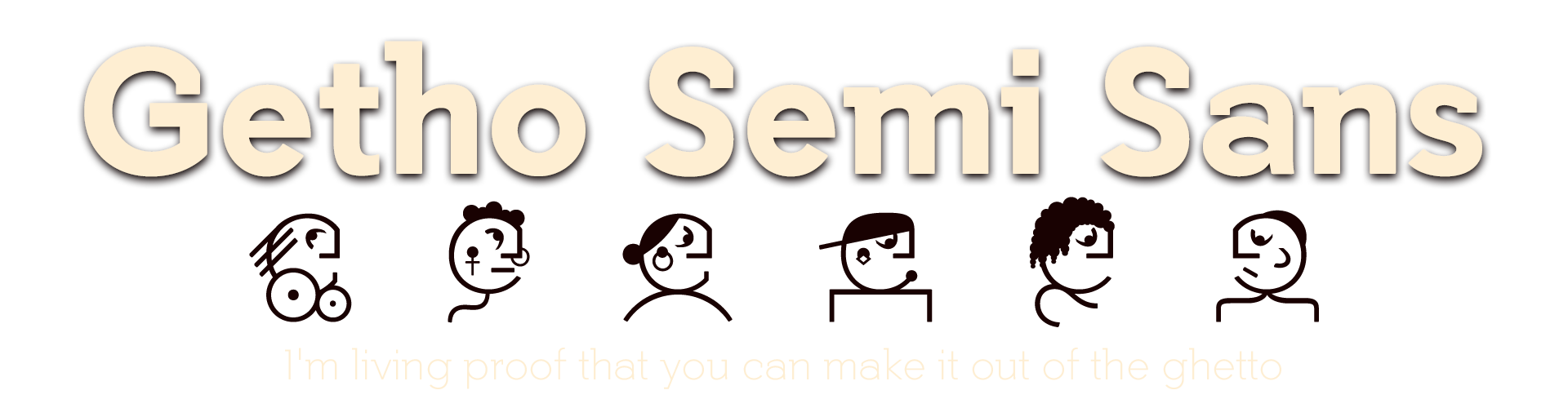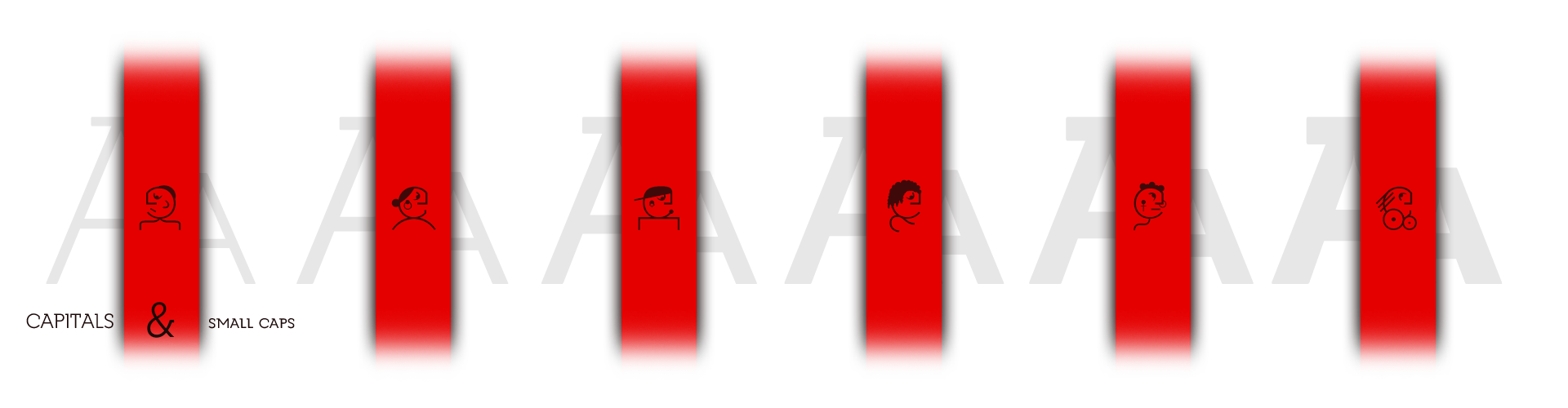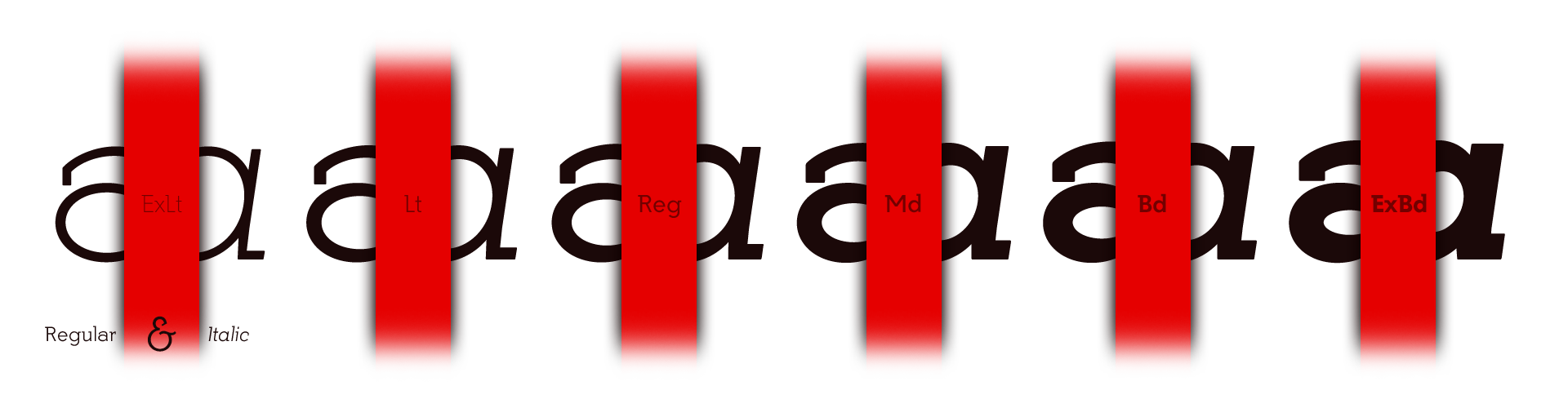
Conceptual typeface
Estilo: Semi Sans, Semi Slab, Versalitas, Geométrica, Corporativa
Proporción: Extra Light, Light, Regular, Medium, Bold & Extra Bold + Italics
Glyphs: 718
Alternates: 181
Funciones OpenType: Additional languages, All Alternates, Alternate Annotation Forms, Capital Spacing, Denominators, Discretionary Ligatures, Extended Fractions, Historical Forms, Historical Ligatures, Inferiors, Kerning, Localized Forms, Numerators, Oldstyle Figures, Optical Size, Ordinals, Scientific Inferiors, Slashed Zero, Small Capitals, Small Capitals From Capitals, Standard Ligatures, Subscript, Superior letters, Superiors, Superscript.
b#) y otros símbolos monetarios.Se trata de una exclusiva tipografía con modulaciones neo-grotescas y máxima legibilidad en cualquier tamaño. La tipografía dispone de letras y números alternativos, versalitas y funciones OpenType avanzadas. He incluido versiones de la tipografía en formato Variable Fonts, sólo con la compra de la familia completa!!
El dibujado de los vectores es minucioso para obtener curvas suaves de aspecto elegante a lo que contribuye también el sutil redondeado de las esquinas, las versiones más gruesas disponen de trampas de tinta en los nudos de las uniones para poder usarlas en pequeños tamaños. La Métrica y el Kerning de todas las versiones las he revisado individualmente para obtener una lectura fluida en cualquier tipo de texto y tamaño.
La tipografía Getho dispone en su versión comercial de un juego de 718 glifos (Latin Extended-A), con soporte para cualquier idioma europeo o centro europeo derivados del Latín. Getho Semi Sans Sans también incluye funciones OpenType (Compatibles con InDesign, QuarkXpress, Photoshop e Illustrator.